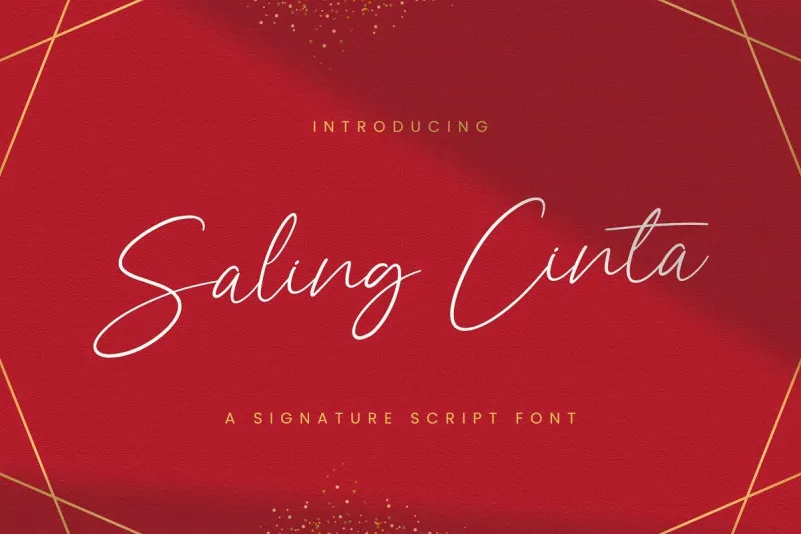
Saling Cinta Handwritten Font – Download Grátis
A Saling Cinta Handwritten Font é uma elegante tipografia script que combina beleza e modernidade. Criada pela StringLabs, esta fonte tem linhas finas e carrega um toque fashion no seu design fino e detalhado. Suas letras são perfeitamente balanceadas e bem feitas, o que a torna ideal para diversas aplicações e projetos de design. Esta font é uma adição perfeita para ideias criativas, destacando-se como um recurso poderoso que enriquece qualquer projeto visual com uma pitada de sofisticação autêntica. Adicionar esta font à sua biblioteca de recursos pode transformar suas criações em verdadeiros elementos centrais do seu design, tornando-as ainda mais únicas e memoráveis.